Canva可画拥有1000+款高质量字体资源,覆盖简繁中、日、韩、法等多语种,风格涵盖书法、手写、复古、优雅、宋体等类型,满足从海报(在新标签页或窗口中打开)标题、品牌Logo(在新标签页或窗口中打开)到正文排版的多元设计需求。无论你是偏好潇洒的毛笔字还是文艺风的钢笔字,都能找到合适的字体。
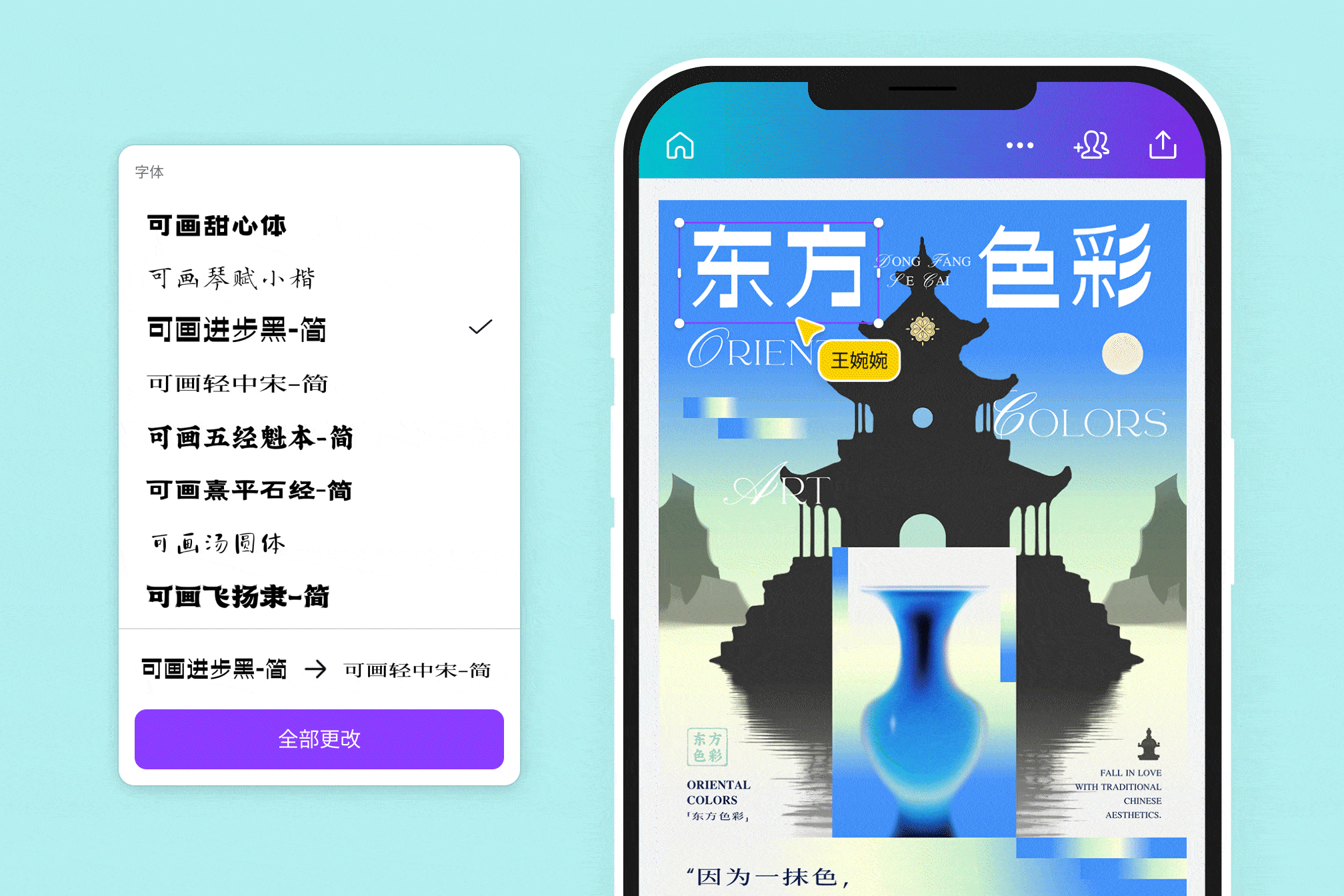
Canva可画支持快速调用字体,无需下载或导入字体,点击文字,再点击字体,即改即用。支持一键替换所有相同字体,节省大量重复操作时间,非常适合多版本测试,方便快速找字用字。
不只是字体资源,Canva可画还拥有文字特效功能,支持描边、投影、霓虹灯、文字背景、波浪弯曲(在新标签页或窗口中打开)等数十种效果。点击一下,实时预览文字效果,操作非常方便。从电商海报、短视频(在新标签页或窗口中打开)字幕到新媒体推文(在新标签页或窗口中打开),用文字特效,轻松提升设计感。